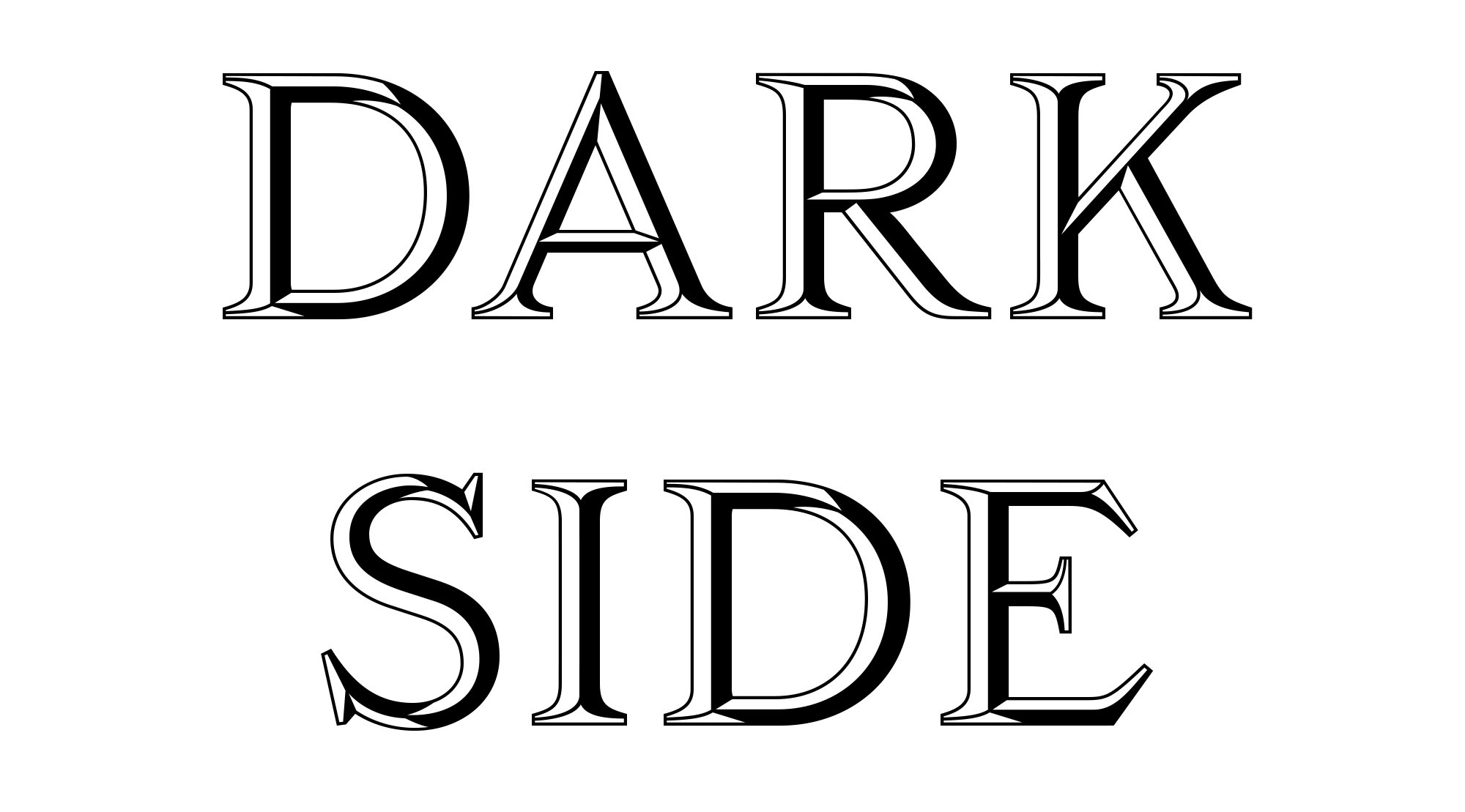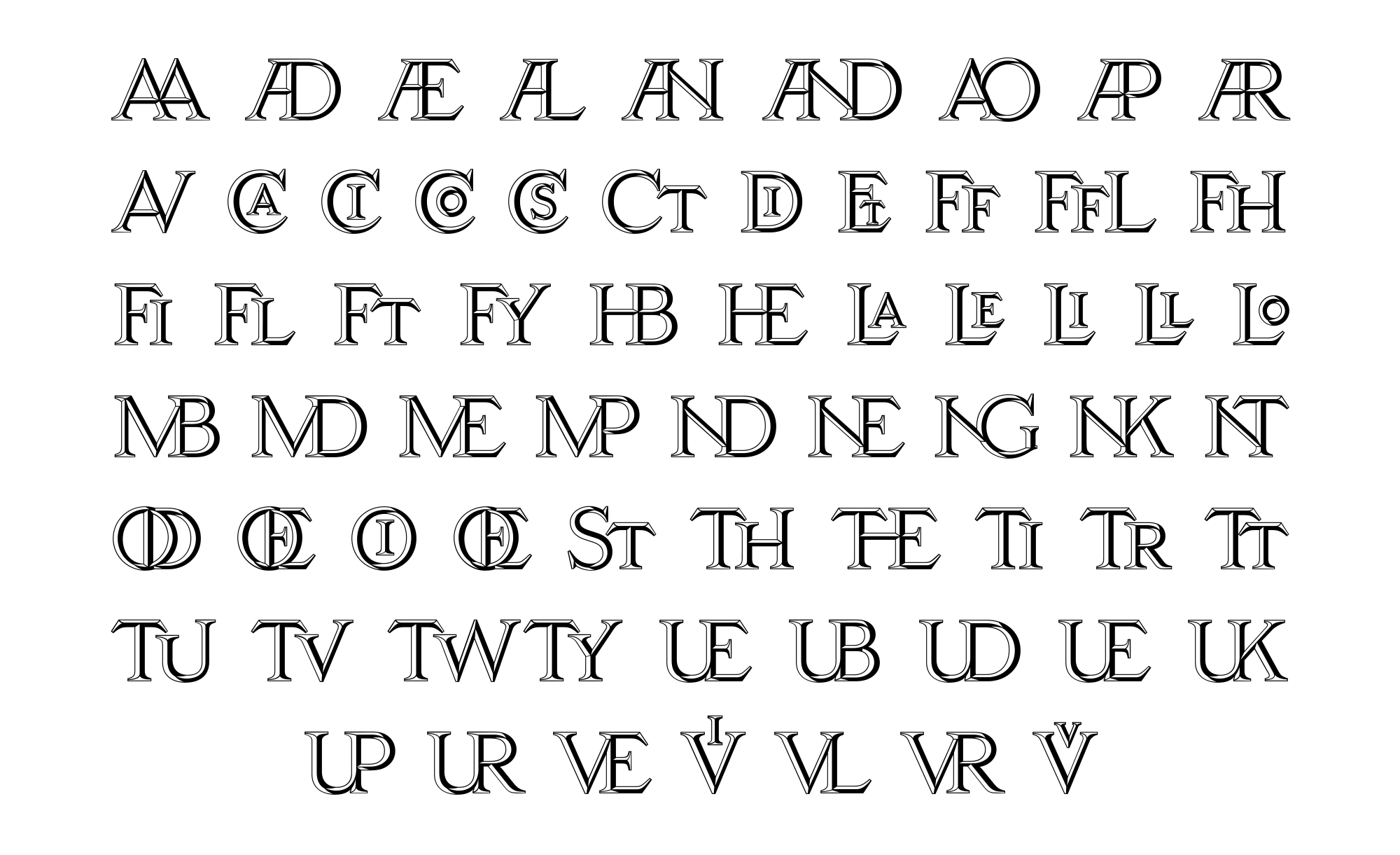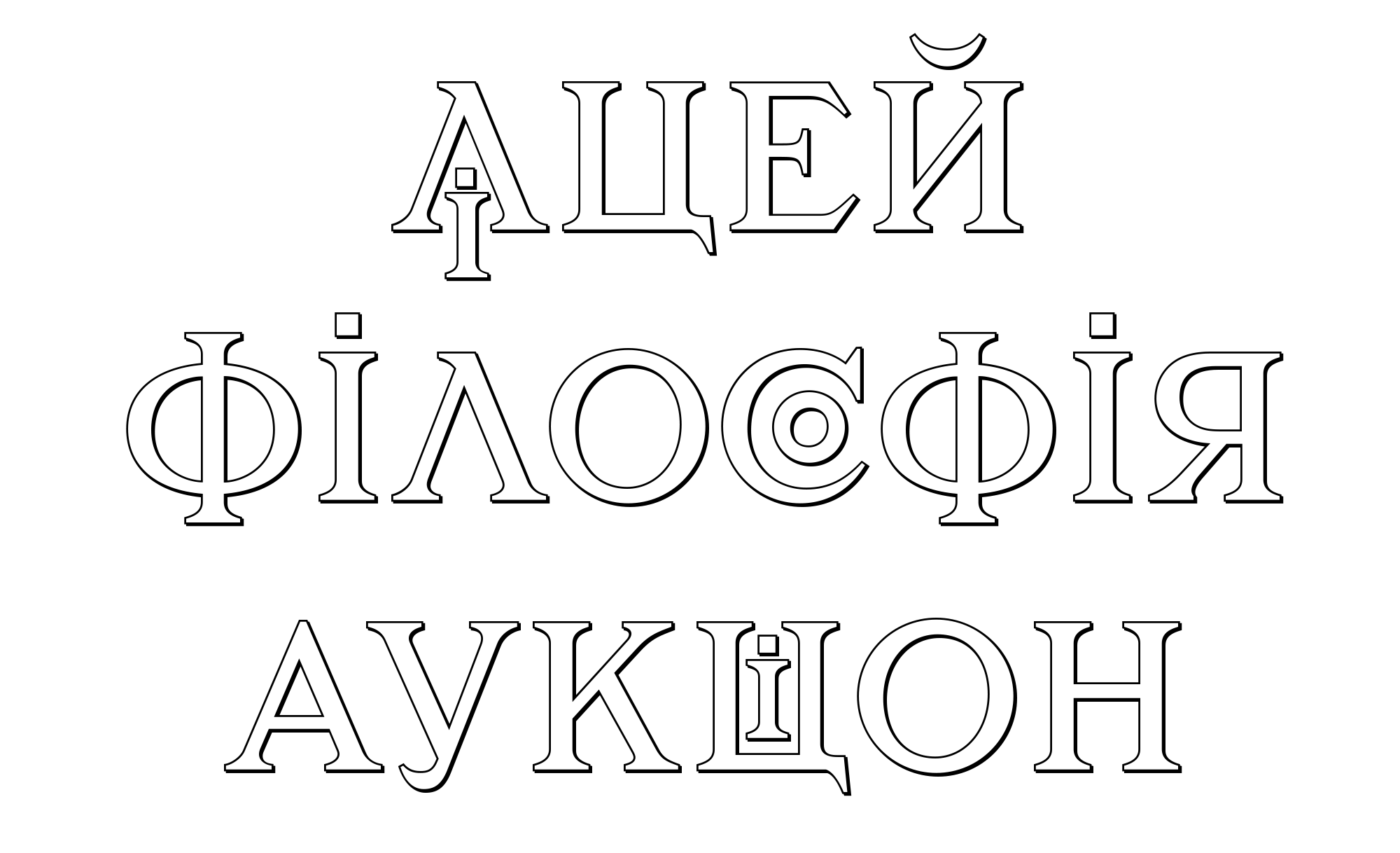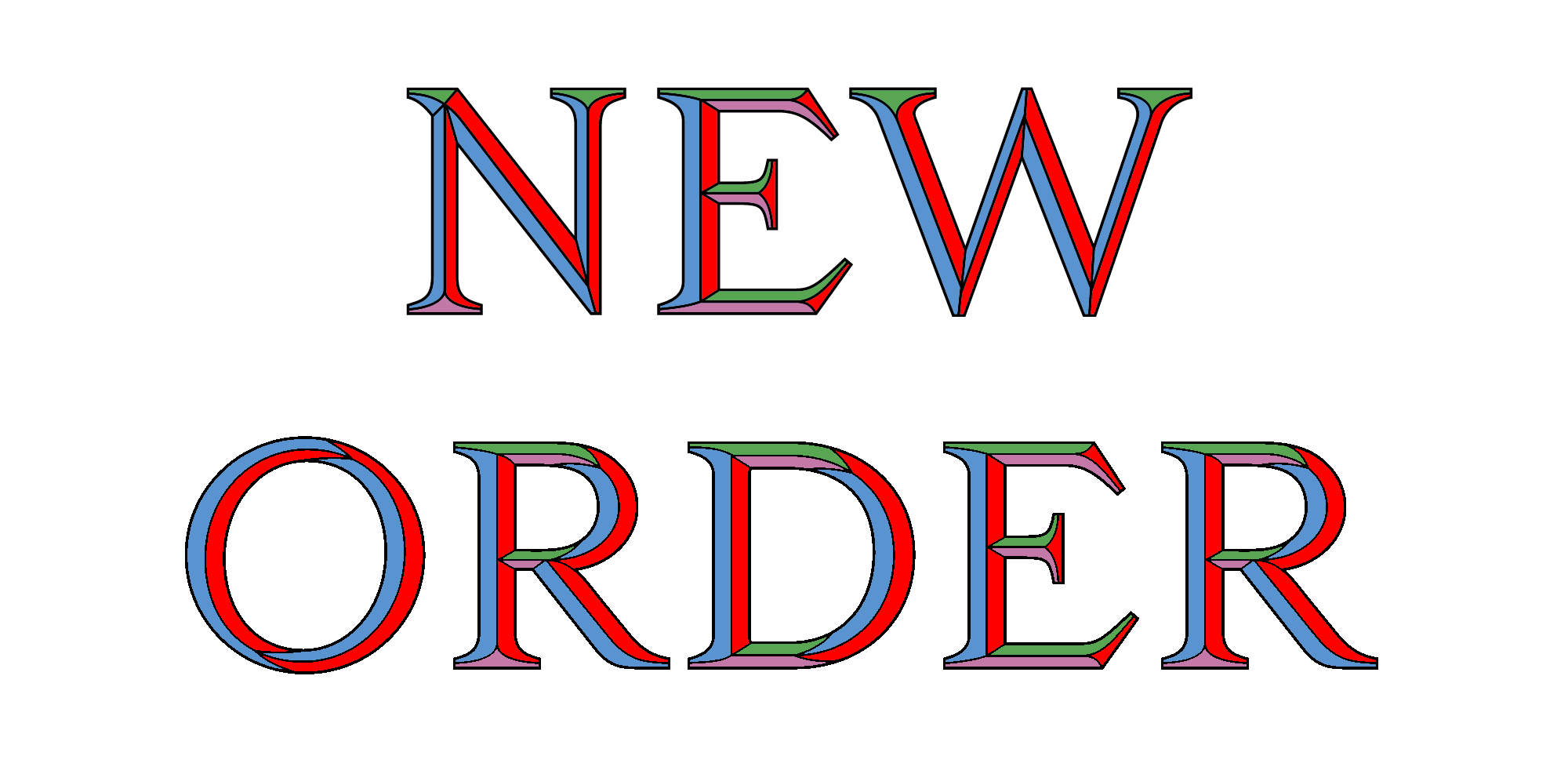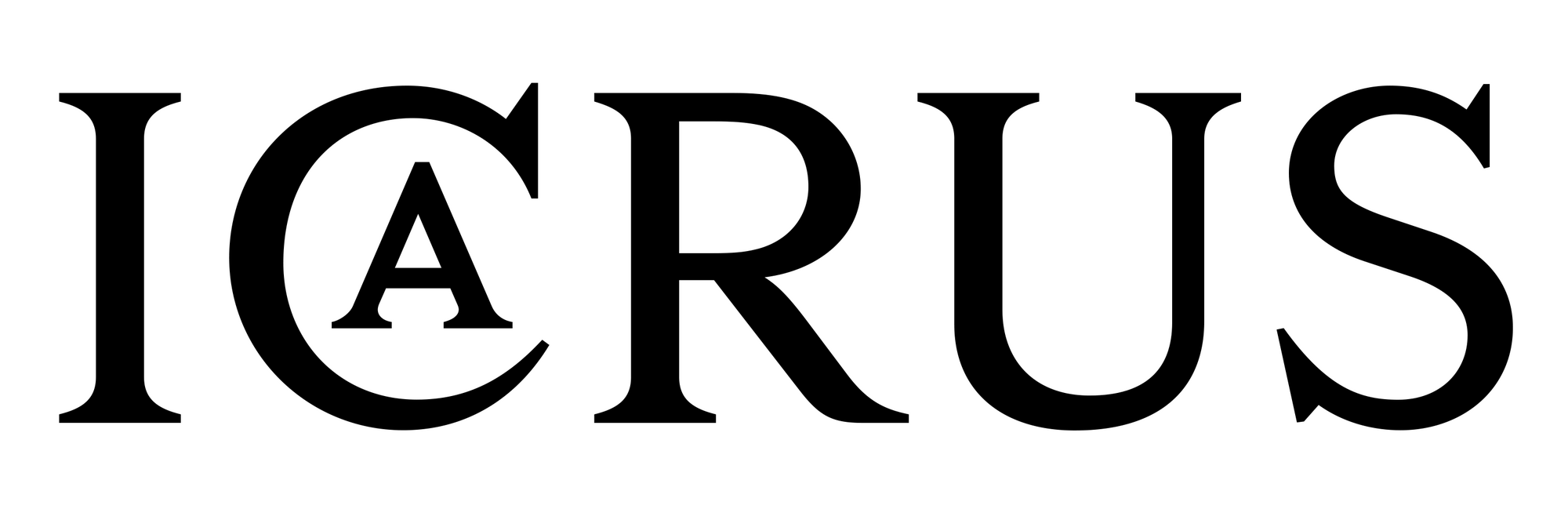
Die KTF Roman ist ein Versalalphabet im Stile einer römischen Monumentalschrift. Grundlage bildeten Beschilderung der U-Bahn in Kiew aus den 1960er-Jahren.
Die 2026 veröffentlichte Neubearbeitung von Yevgeniy Anfalov und Anna Kovalenko verfügt über die Varianten Roman, Outline, Shadow, BlackWhite und eine mehrfarbige Variante (Color).